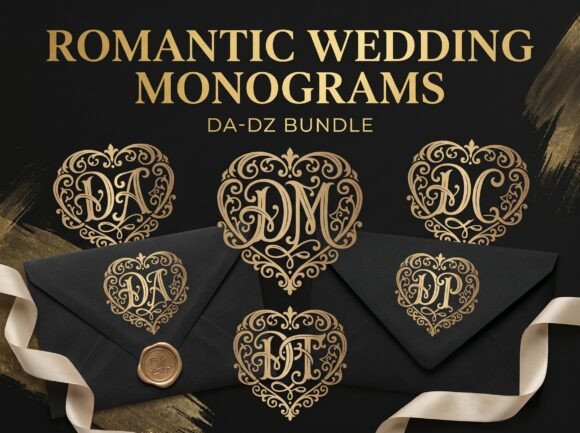
26 Romantic Wedding Monogram DA-DZ
Việc tìm kiếm các thành phần thiết kế phù hợp có thể là một thách thức, nhưng 26 Romantic Wedding Monogram DA-DZ cung cấp một bộ sưu tập đặc biệt giúp nâng tầm công việc của bạn ngay lập tức.
Cho dù bạn đang tạo sản phẩm POD (In theo yêu cầu), thiệp mời đám cưới hay đồ họa mạng xã hội, 26 Romantic Wedding Monogram DA-DZ đều là một sự lựa chọn lý tưởng.